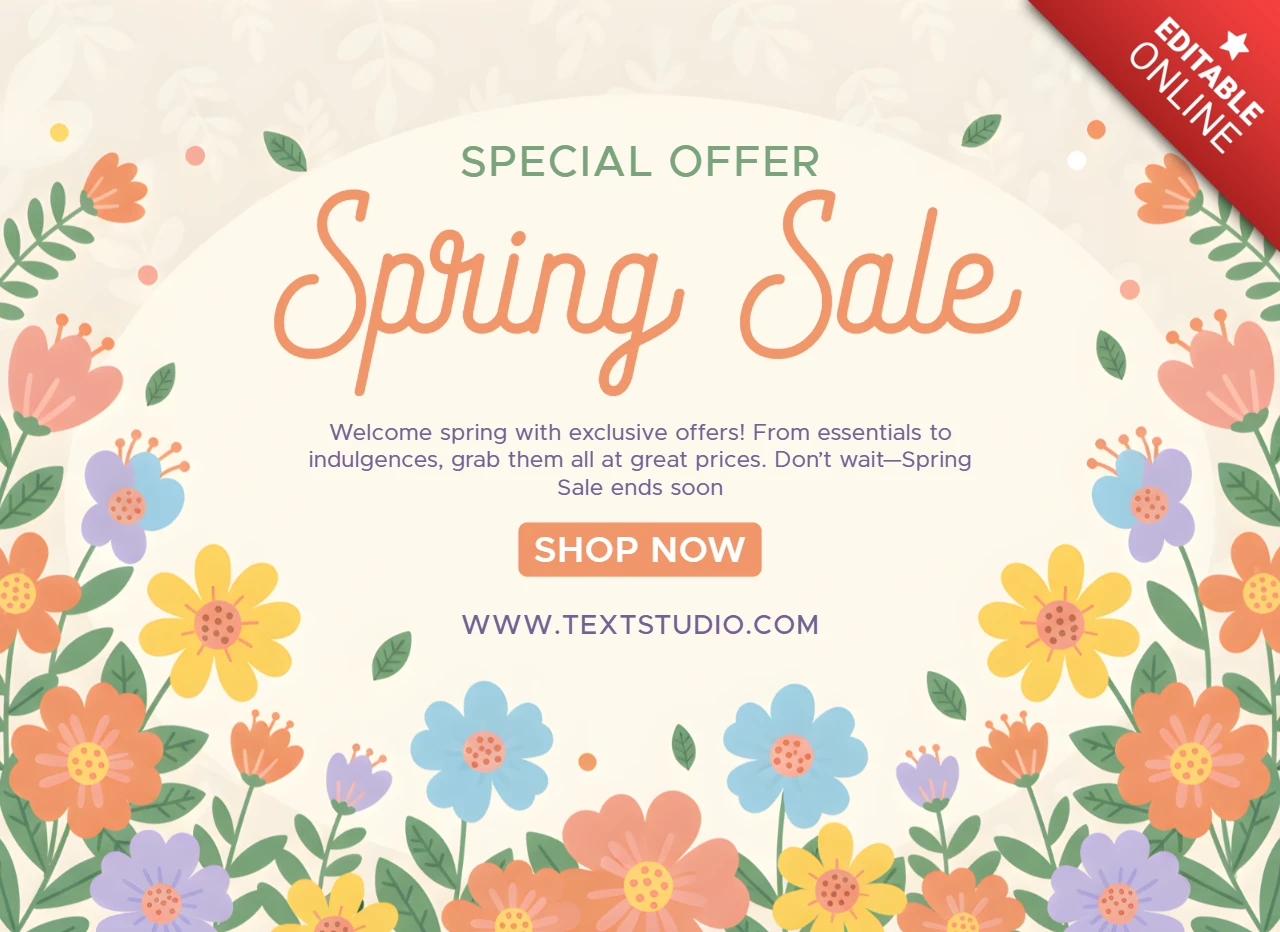
Affiche promotionnelle de vente de printemps avec une bordure florale, une typographie en gras et des offres à durée limitée.
Éditer dans Design Studio Télécharger en JPGÉlevez vos projets créatifs avec notre offre limitée sur des modèles à thème floral, parfaits pour des cartes de vœux et des affiches, mettant en avant une typographie audacieuse et des couleurs pastel inspirées du printemps.